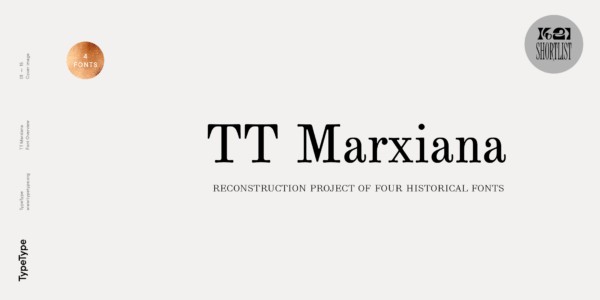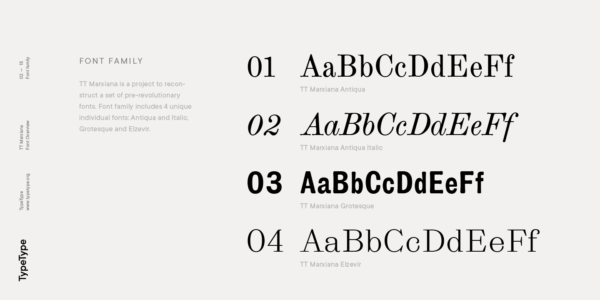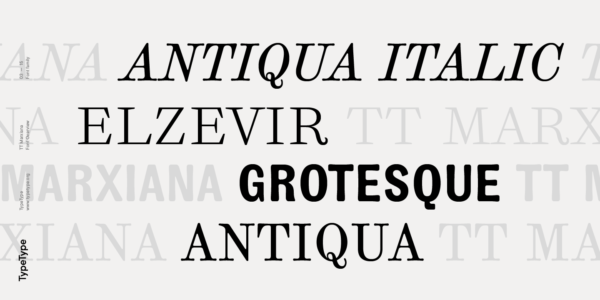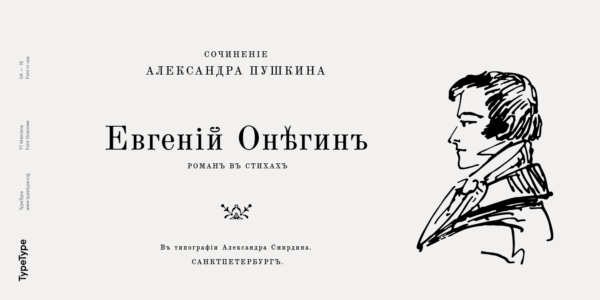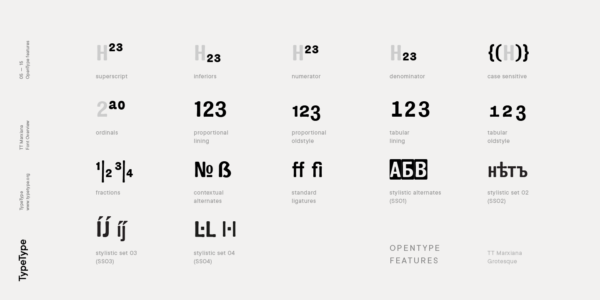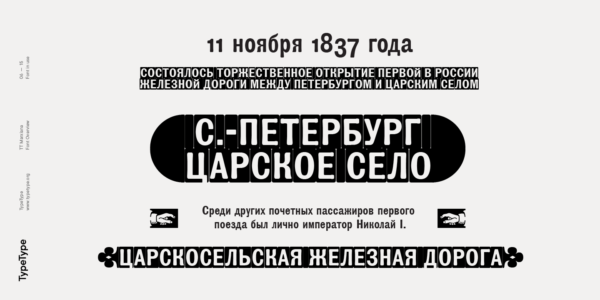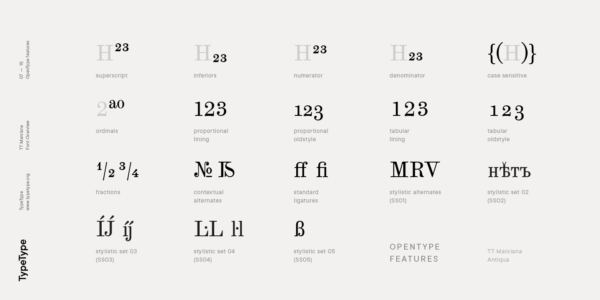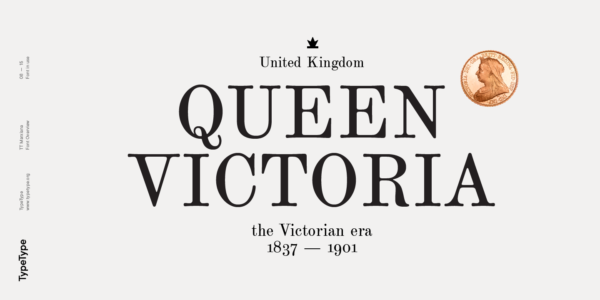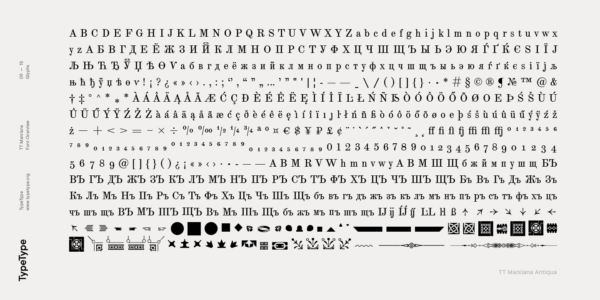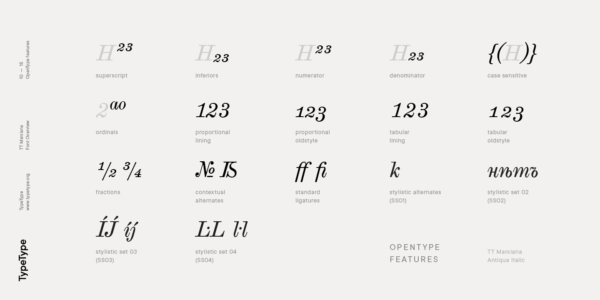
TT Marxiana — ТТ Марксиана
Произносится «ТТ Марксиана». «Marxiana» — производное слово от имени собственного «Маркс». Шрифт назван в честь Адольфа Фёдоровича Маркса — основателя типографии и издательства, выпускавшего в Санкт-Петербурге журнал «Нива», шрифты из которого были взяты за основу при создании этой гарнитуры . Буквы «TT» являются аббревиатурой названия компании.
TT Marxiana — набор из трёх реконструированных дореволюционных шрифтов, которые использовались в вёрстке журнала «Нива» 1887 года.
TT Marxiana Antiqua has an interesting stylistic set that imitates the old setting and in which some of the signs are made with deliberate sticking or roughness. Using this set will provide an opportunity to further simulate the setting of that great time.
TT Marxiana is a project to reconstruct a set of pre-revolutionary fonts that were used in the layout of the Niva magazine, published by the St. Petersburg publishing house A.F. Marx. In our project, we decided to focus on a specific set of fonts that were used in the preparation and printing of the Niva magazine in 1887, namely its Antiqua and Italic, Grotesque and Elzevir.
TT Marxiana в дизайне
О гарнитуре TT Marxiana
TT Marxiana является проектом по реконструкции набора дореволюционных шрифтов, которые использовались в вёрстке журнала «Нива», издававшемся Санкт-Петербургским издательством А.Ф. Маркса. В нашем проекте мы решили остановиться на конкретном наборе шрифтов, которые использовались в изготовлении и печати журнала «Нива» 1887 года выпуска, а именно на его антикве и италике, гротеске и эльзевире.
В рамках проекта TT Marxiana мы стремились придерживаться строгой историчности и сохранить максимальную близость к бумажному первоисточнику. Мы старались избежать какого-либо «осовременивания» шрифтов, если за таковое конечно не считать работу с кернингом, внедрение OT фич и создание ручного хинтинга. В итоге с гарнитурой TT Marxiana современный дизайнер получает полноценный и функциональный набор разных шрифтов, позволяющий современными методами и с помощью современных программам создать, например, журнал с дизайном, характерным для конца 19 века.
Проект TT Marxiana стартовал в конце лета 2018 года и с самого своего начала выходил за рамки традиционных проектов от TypeType из-за важного фактора по сохранению исторической идентичности. Так как до этого момента мы никогда прежде не реконструировали шрифт по историческим бумажным источникам и с таким уровнем проработки и вниманию к деталям, то на реализацию этого проекта у нас ушло два года. Подробнее о всех этапах проекта можно почитать в нашем блоге, а тут мы кратко расскажем про получившийся результат.
TT Marxiana Antiqua — это шрифт с засечками в стиле шотландских антикв, при рисовании которой бережно сохранены некоторые артефакты, полученные при печати, а именно точечное усиление, небольшая деформация букв и другие визуальные нюансы. TT Marxiana Antiqua имеет интересный стилистический набор, имитирующий старинный гарнитур, в котором некоторые знаки выполнены с намеренным залипанием или шероховатостью. Использование этого набора даст возможность еще больше имитировать обстановку того великого времени.
TT Marxiana Grotesque представляет собой довольно плотный и жирный старый гротеск. Его рисунок также максимально сохранил дефекты полученные при печати и свойственные его бумажному референсу. Кроме дореволюционной орфографии в составе TT Marxiana Grotesque есть декоративный сет с вывороткой. Это набор прописных знаков, цифр и пунктуации, который позволяет набирать инверсные заголовки, т.е. печатать белым по-чёрному. В результате использования этого сета получается текст, лежащий на чёрных плашках — такой способ акциденции был очень характерен для печати рекламы на рубеже веков. Кроме того, для этого сета было отрисовано около 30 декоративных заглушек-указателей: стрелки, руки, трефы и т.д.
TT Marxiana Elzevir — титульный или заголовочный шрифт, представляет собой компиляцию монастырского Elzevir, который активно использовался в журнале «Нива» для всех его печатных изданий. В отличие от основной антиквы, TT Marxiana Elzevir имеет более четкие формы, и влияние деформаций от типографской печати не так заметно в формах его знаков. Это связано, прежде всего, с особенностями его рисунка и с тем, что он обычно использовался в качестве заголовочного шрифта и печатался в больших размерах. Высота строчных и прописных знаков у эльзивир начертания такая же, как у основной антиквы, но шрифт более контрастный и светлый, в нем много белого и, в отличие от антиквы и гротеска, много острых углов. Эксклюзивной особенностью TT Marxiana Elzevir является альтернативный набор прописных символов со свошами.